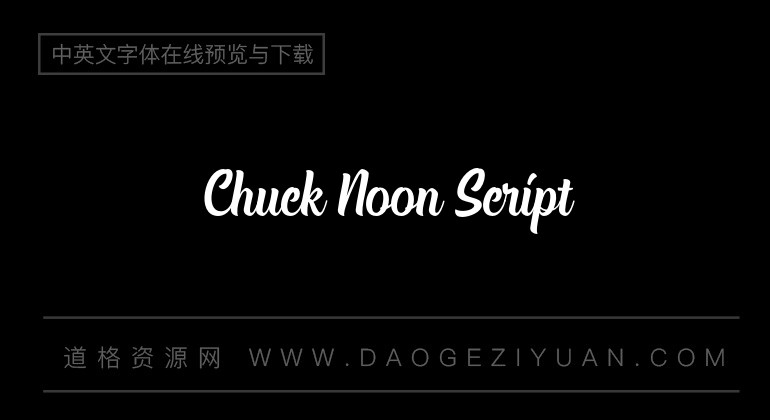
Chuck Noon Script
Chuck Noon Script 是一款英文手写体字体,它具有温暖的、时尚的外观,可以为设计师的作品增添独特的气质。它的字体外观自然,富有表情,具有良好的可读性,可以为您的设计提供温暖而又优雅的氛围。它拥有丰富的字形,可以满足您不同的需求,可以用于印刷、网页设计、平面设计等领域。
Chuck Noon Script是一款非常不错的手写艺术字体,具有很好的视觉感,适合于文化类的宣传设计、商业类品牌的广告和产品包装设计以及个性化文字排版等较多场景。